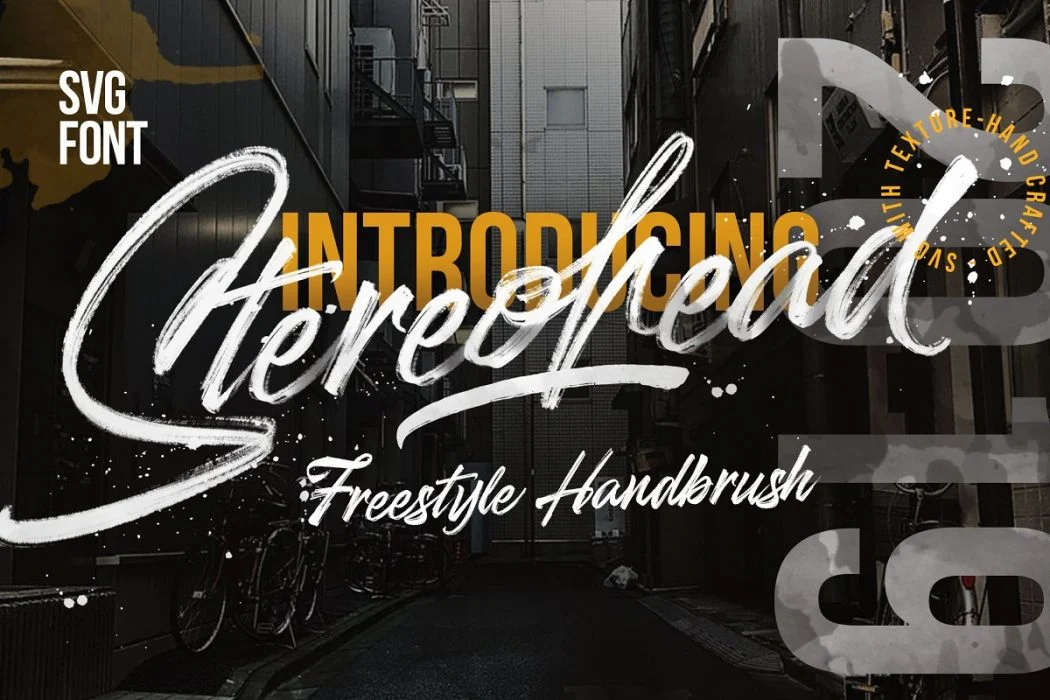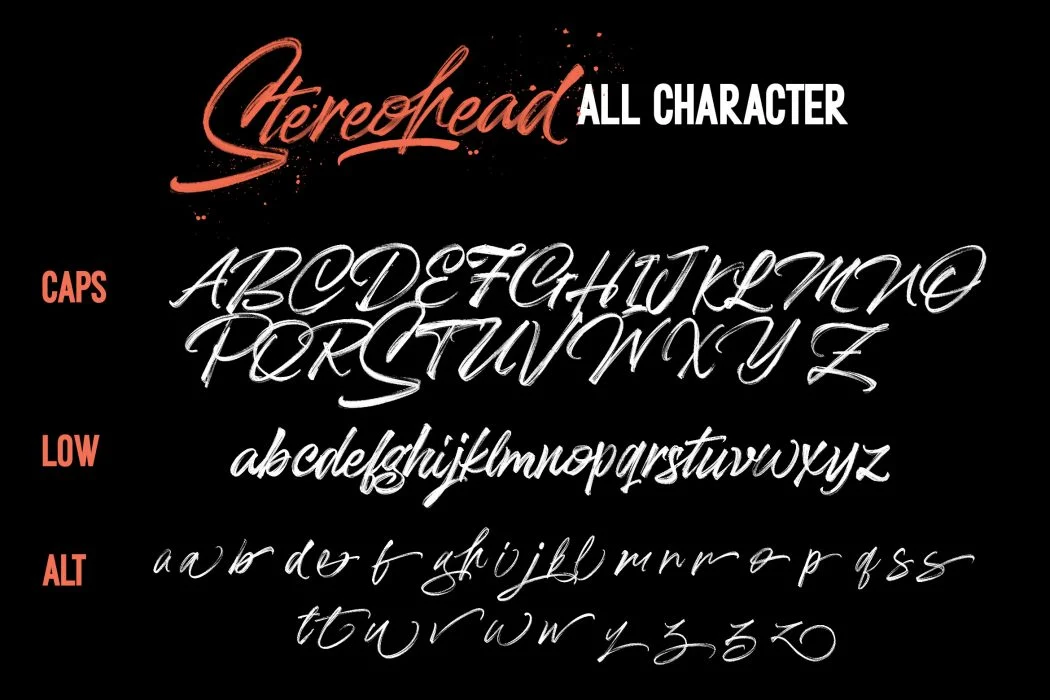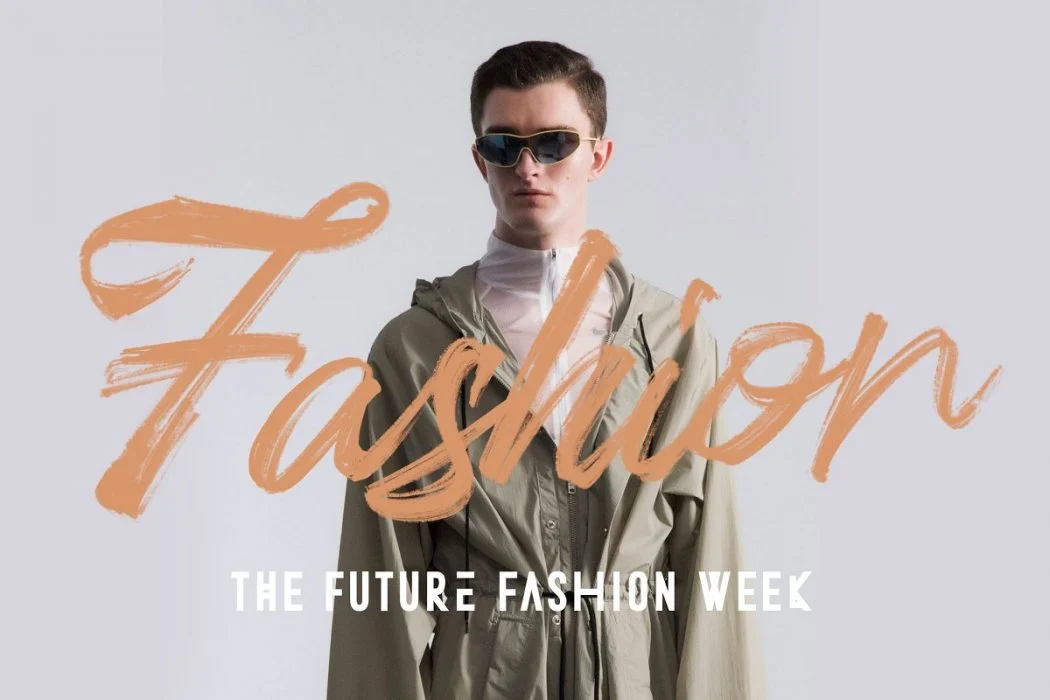
فونت قلممویی انگلیسی Stereohead | فونت SVG دستنویس
تایپوگرافی و طرحهای دستنویس خود را با اصالت بینظیر قلمموی واقعی جاودانه کنید! پکیج فونت قلمموی دستنویس استریوهد (Stereohead – Stylist Brush SVG Font) یک فونت فوقالعاده مدرن با بافت خیس و طبیعی قلممو است که به لطف تکنولوژی فونتهای SVG، تمام شفافیتها و جزئیات رنگآمیزی دستی را در خود جای داده است. این پکیج شامل فرمتهای OTF، TTF، فونتهای وب، به همراه فمیلی فونت مکمل Metafora Sans است تا طرحهای لوگو، امضا، پوسترهای تبلیغاتی و بستهبندیهای شما حسی کاملاً دستساز، پریمیوم و بیرقابت به خود بگیرند.
فونت قلمموی دستنویس Stereohead فونت Font
خلق تایپوگرافی و لوگوهای بینظیر با بافت واقعی قلمموی خیس و شفافیت طبیعی
استفاده از فونت قلمموی دستنویس استریوهد به طراحان گرافیک و متخصصین برندینگ این امکان را میدهد که بدون نیاز به طراحی دستی پیچیده، تایپوگرافیهایی با بافت رنگآمیزی شده و طبیعی خلق کنند. تکنولوژی پیشرفته فونت تمام جزئیات لکههای رنگ و شفافیتهای قلمموی خیس را مستقیماً درون کاراکترهای فونت ذخیره کرده است.
ویژگیهای شاهکار فونت قلمموی دستنویس استریوهد
امکاناتی که پروژه و خروجی کارهای شما را بیدردسر میسازد
تکنولوژی فونت فونت با بافت واقعگرایانه HD
این فونت از قابلیتهای مدرن فونت جهت ثبت تمام جزئیات، شفافیتها (Transparency) و گذر نور روی بافت قلمموی خیس بهره میبرد که خروجی تایپوگرافی را دقیقاً شبیه به یک اثر نقاشی شده با دست میکند.
فمیلی فونت مکمل Metafora Sans
وجود فمیلی فونت مکمل Metafora Sans درون پکیج، نیاز شما را به پیدا کردن فونتهای ثانویه برای توضیحات یا کپشنها برطرف کرده و بالانس بصری فوقالعادهای ایجاد میکند.
کاربرد نامحدود در پروژههای لوکس و برندینگ
انتخابی ایدهآل برای طراحی امضاهای تجاری، لوگو، بستهبندی محصولات لاکچری، کاور موزیک، پوسترهای تبلیغاتی، کارت پستال و محتوای شبکههای اجتماعی.